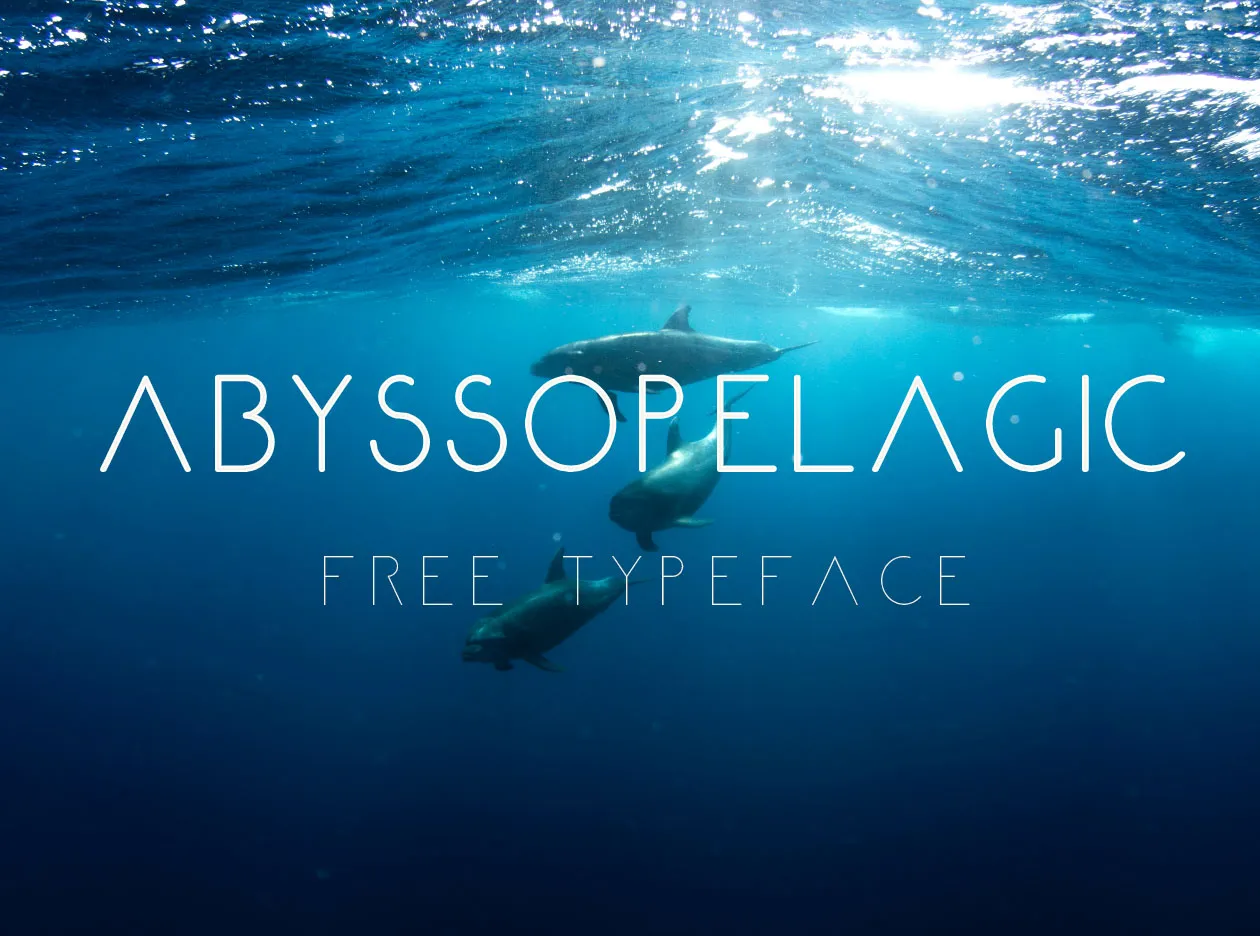
Abyssopelagic Font – Download Grátis
Abyssopelagic Font é uma elegante tipografia do tipo sans-serif que foi projetada para maximizar seu espaço quando estilizada. Seu designer, Hamilton, capturou a essência de sua inspiração inicial em um desenho feito à mão sobre papel, resultando num resultado sofisticado e moderno. Utilizando Adobe Photoshop CC, o design dos caracteres foi criado antes de exportar para High-Logic Font Creator. Esta fonte não apenas oferece uma aparência impecável quando espaçada, mas também exibe uma grande diversidade e originalidade em cada letra. Com sua estrutura simples e arredondada, Abyssopelagic atinge um equilíbrio perfeito entre clareza de leitura e a modernidade vibrante. Ideal para aplicações digitais que buscam um estilo clean e contemporâneo, esta fonte se destaca tanto nas redes sociais quanto em sites profissionais ou editoriais. Seja você designer, produtor gráfico ou qualquer pessoa com um projeto de design à vista, Abyssopelagic é uma escolha perfeita para adicionar um toque único ao seu trabalho.